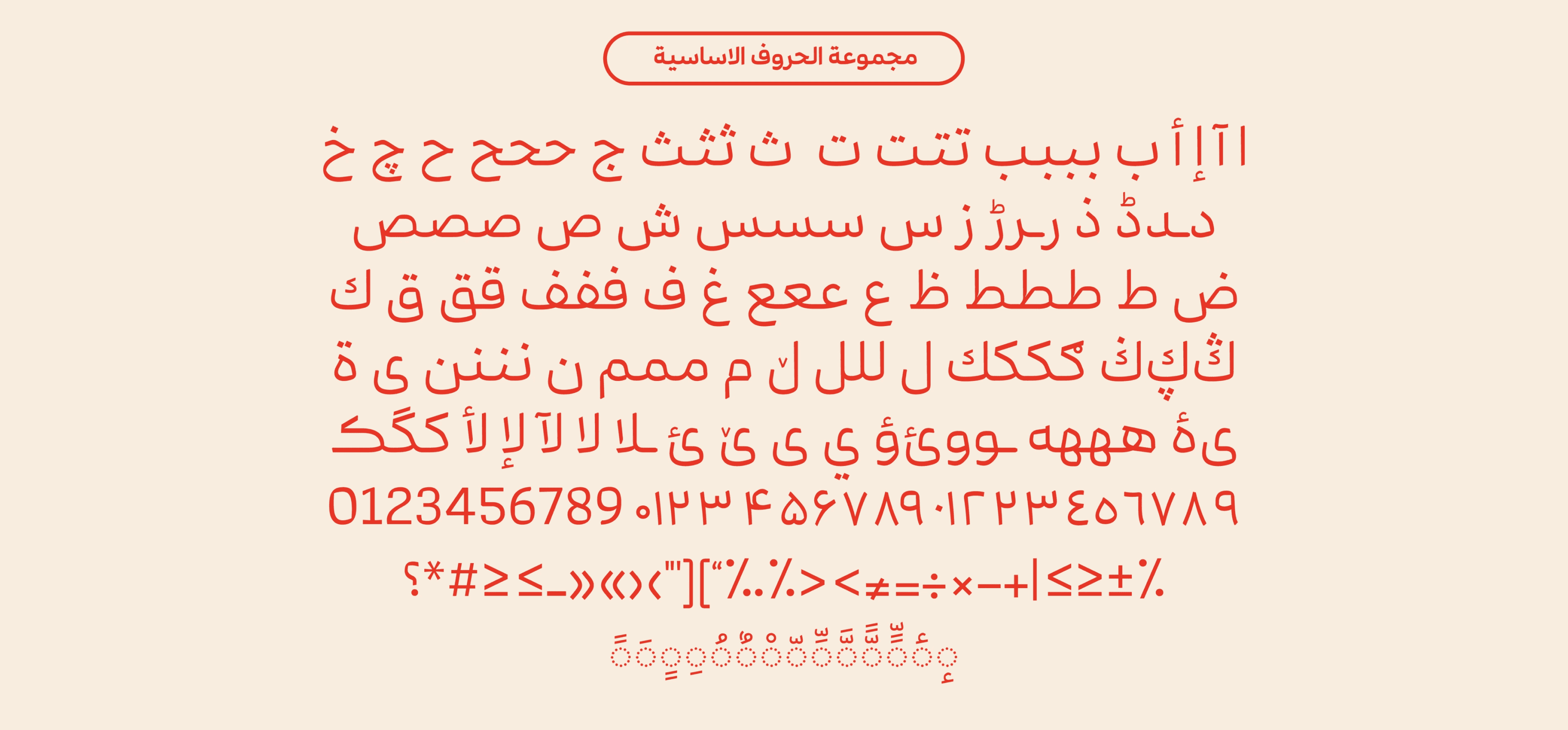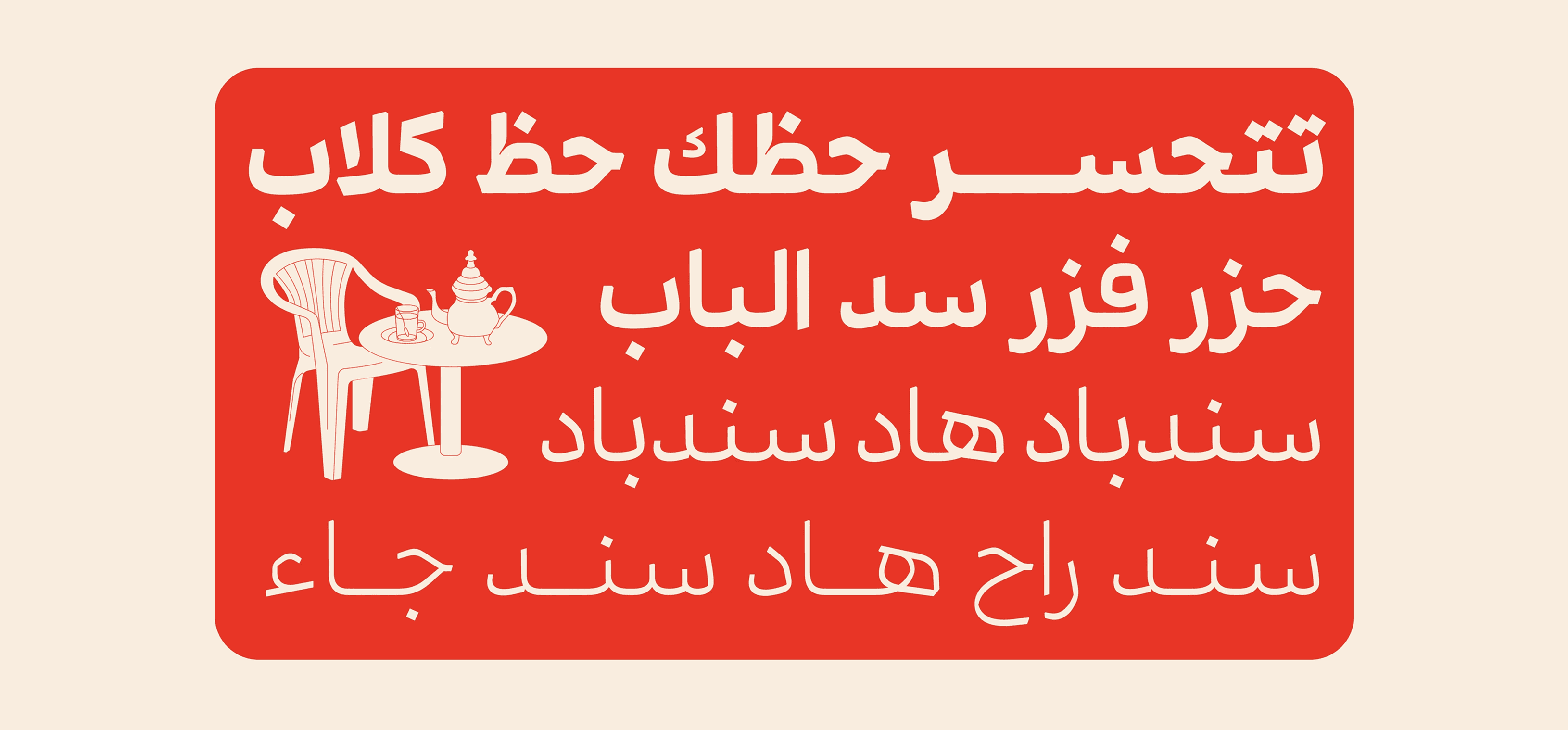
ميستيكا – Mestika
ميستيكا هو اسم لنوع من التوابل الصمغية، ويعني "الصمغ" في اللغة العربية. سُمّي الخط بهذا الاسم نظرًا لما يجمعه من حواف حادّة وتوصيلات خطّية انسيابية، ما يمنحه طابعًا مميزًا وفريدًا يُبرز حضوره في التصاميم.
يتميّز ميستيكا بتصميم حاد منخفض التباين، ويأتي بتسعة أوزان تجعله مناسبًا للنصوص والعناوين على حد سواء.
الخط نتاج تعاون بين المصمّم الإيراني كامياب جعفري والمصمّم العربي، ويقدّم تصميمًا عصريًا غنيًا بالربط الطباعي (ligatures) والخصائص المتقدّمة لتحسين المحاذاة وضبط التشكيل.
خيار مثالي لمن يبحث عن توازن بين الحداثة والطابع الكلاسيكي في الكتابة العربية.